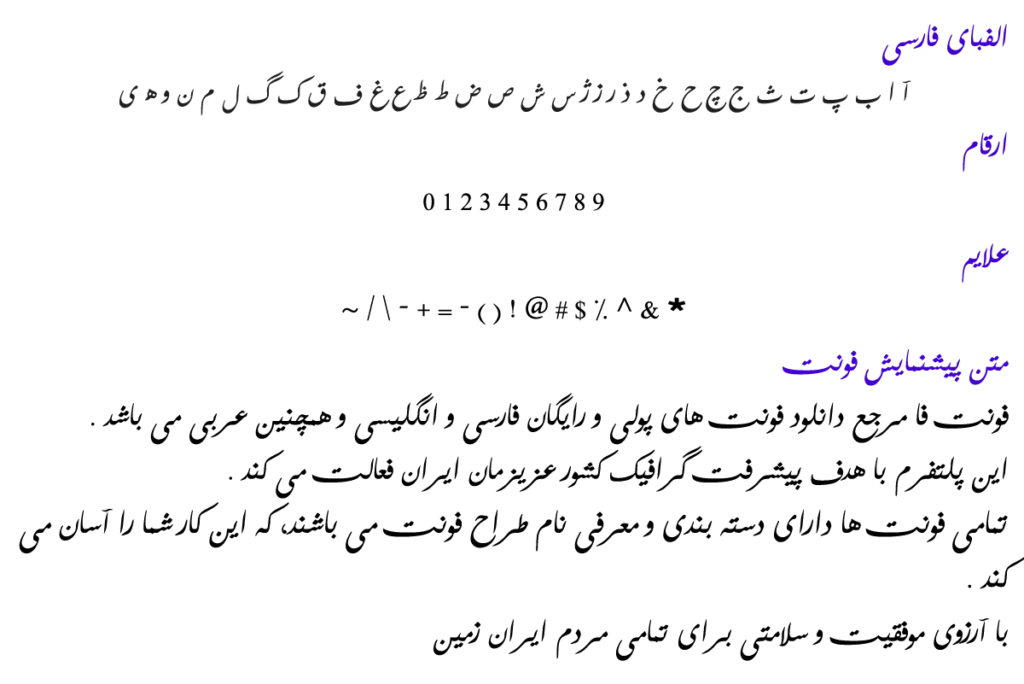
فونت فارسی ام جی فارسی – Mj Farsi
مجموعه فونت: فونت سری Mj
طراح فونت: مجتبی کیا نوع فونت: فونت خوشنویسی
پیشنمایش فونت ام جی فارسی
توضیحات و معرفی فونت ام جی فارسی
فونت فارسی ام جی فارسی ( Mj Farsi ) از مجموعه فونت های سری Mj می باشد، همچنین نوع فونت خوشنویسی می باشد.
فونت فوق العاده زیبای معرفی شده توسط مجتبی کیا در سال 1390 طراحی و ساخته شده است.
این تایپ فیس مشابه فونت شکسته و فونت نسخ می باشد.
همچنین فونت در دو وزن معمولی و Outline است.
در لیست زیر می توانید وزن این فونت فوق العاده زیبا را ببینید.
- Mj Farsi Normal
- Mj Farsi Outline
در تصویر زیر شعر ایرانی وطن را که با این تایپ فیس نوشته شده است را می توانید تماشا کنید.